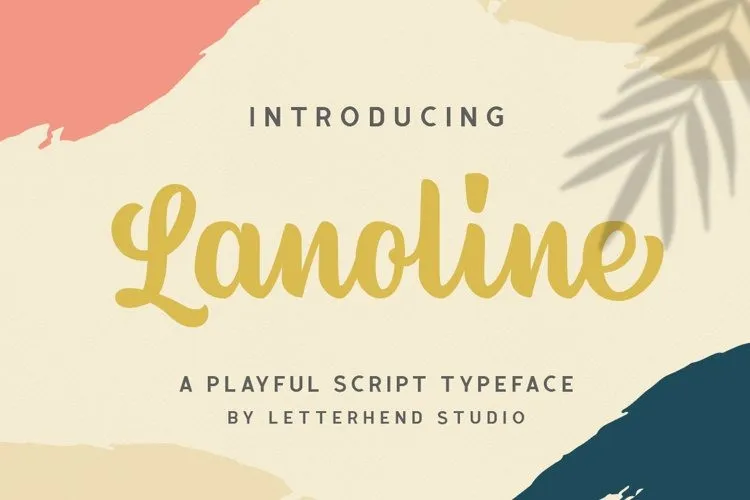
Esta é uma fonte script criada pelo designer letterhend para os amantes do estilo tipo logotipo. Com seu aspecto casual, a Lanoline ainda mantém uma aparência impactante e destaca-se entre as demais. Os swashes adicionados não apenas tornam o design único, mas permitem que você monte sua própria personalização ao criar seu próprio logotipo. Esta font é perfeitamente adequada para headlines, logotipos, roupas, convites, marcações, embalagens, anúncios e muito mais. Ela inclui maiúsculas e minúsculas, pontuação, símbolos, números, conjuntos alternativos de estilização, ligaturas e suporta múltiplas línguas. Com sua linguagem informativa e convidativa, a fonte Lanoline é um recurso indispensável para designers gráficos que buscam uma nova opção em sua coleção. Se você tiver alguma idéia ou feedback sobre esta fonte, fique à vontade para compartilhar com o designer ou através de contato direto. Acreditamos que ela pode fazer toda a diferença na forma como você expressa seu trabalho visual.